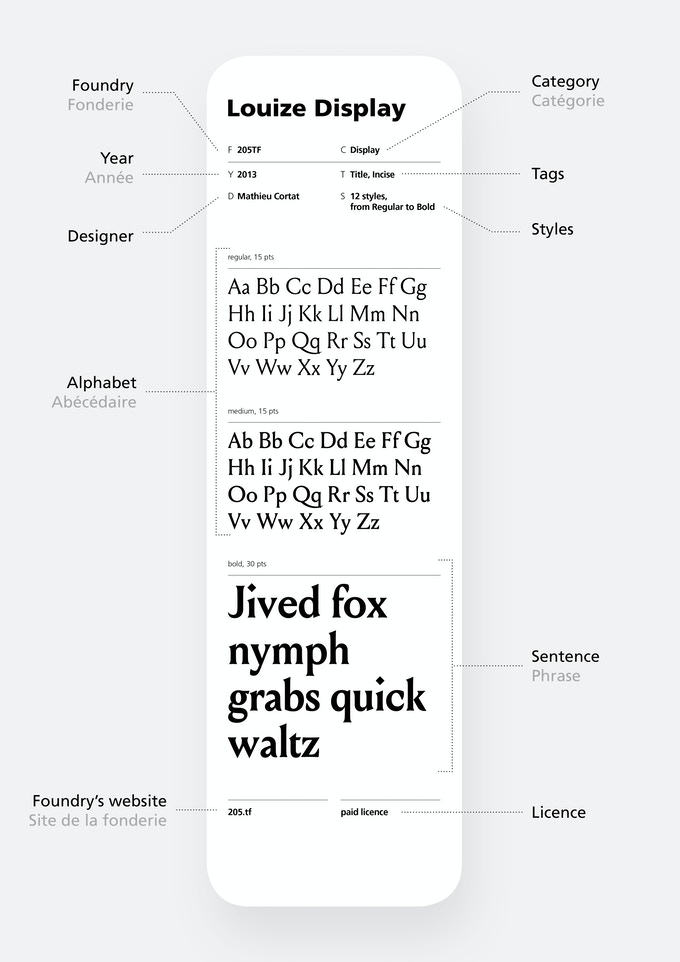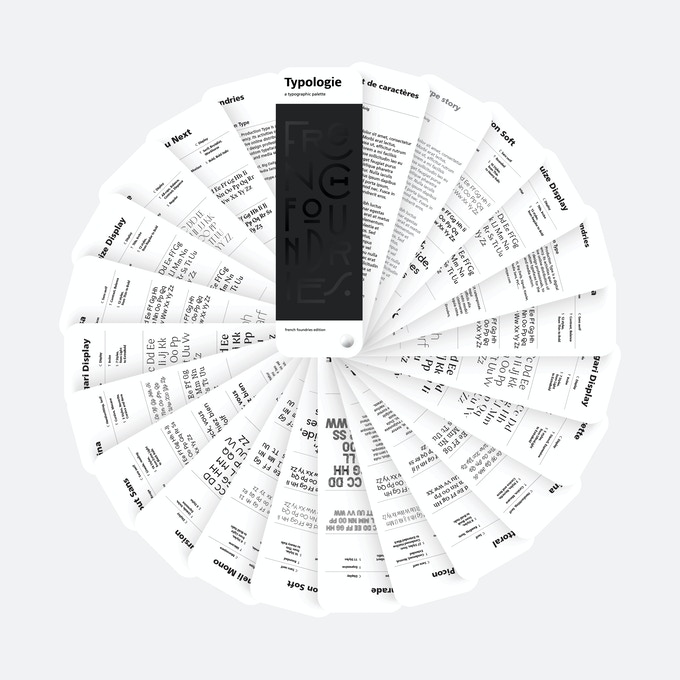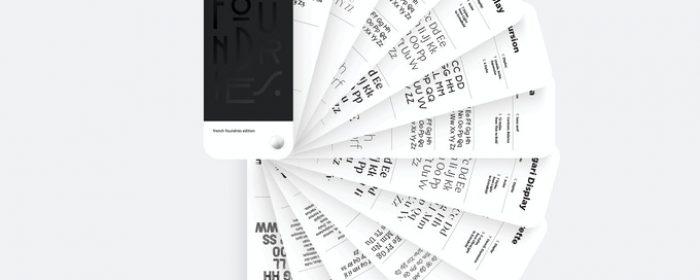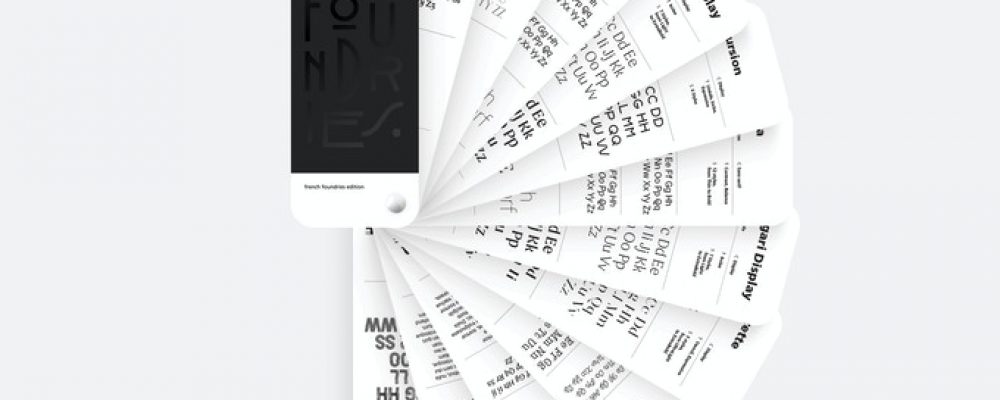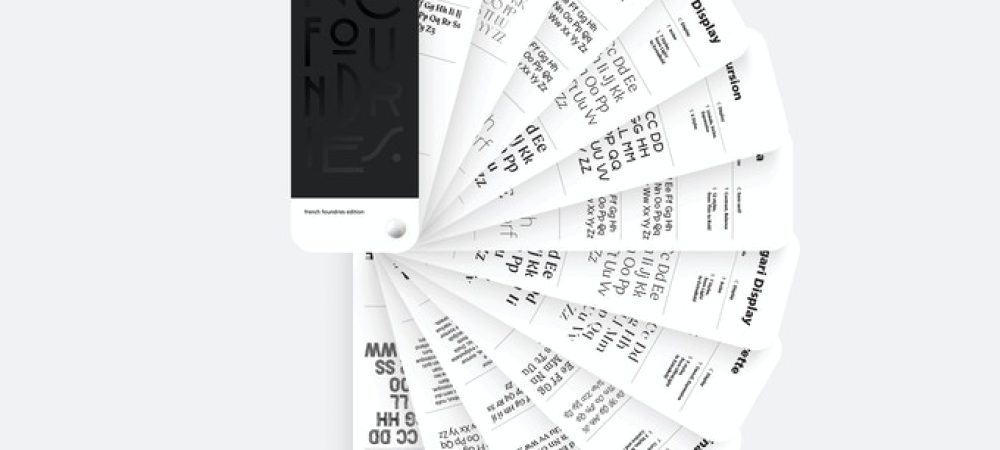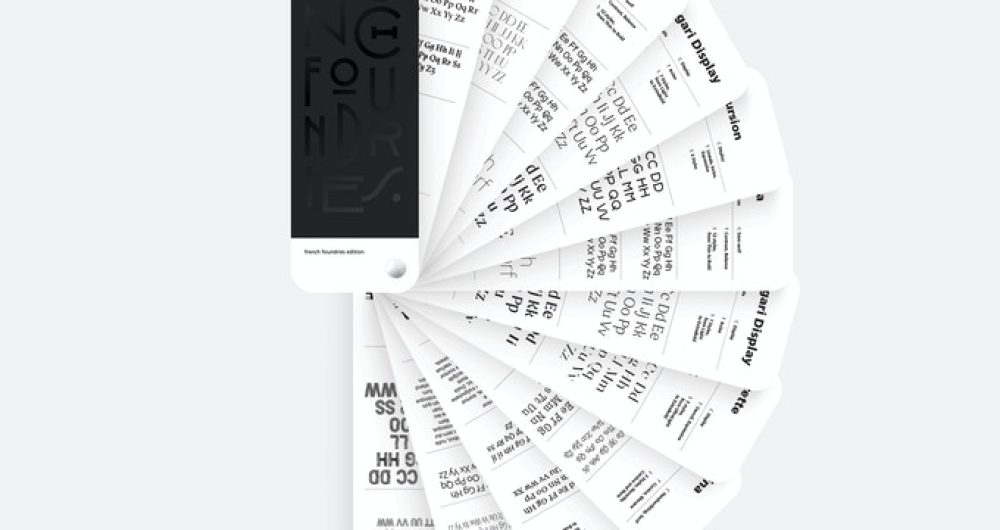
Un nuancier spécialement conçu pour les amoureux de la typographie
Si vous nous suivez régulièrement, vous connaissez notre goût particulier pour la belle typographie. En effet, la calligraphie est un art qui permet de laisser transparaître des émotions, un caractère, mais c’est surtout un formidable outil de communication.
Aujourd’hui je vous présente Typologie, un livre sous la forme d’un nuancier Pantone qui raconte les finesses et les histoires des typographies. Imaginé par Pierre-Yann Lallaizon, ce livre original vous transportera dans un nouvel univers typographique, vous forçant ainsi à sortir de votre zone de confort artistique. En effet, tous les créatifs ont leur propre palette de polices de caractères et ils sont, généralement, plutôt réticents au changement. C’est le constat que l’auteur a fait et qu’il à voulu briser à travers ce livre. Quelle meilleure combinaison pouvait-il y avoir entre un nuancier, représentation parfaite de la recherche d’un atout créatif (une couleur) et la typographie ?
Sa forme unique permet donc aux créatifs de faire matcher des typographies entre elles, et de trouver de nouvelles combinaisons facilement. Plus qu’un outil de travail, c’est également un bel objet qui est assez cool à poser dans sa bibliothèque ou sur son bureau. Le nuancier se décompose d’ailleurs en plusieurs catégories :
• Typographies Serif
• Typographies Sans Serif
• Typographies Display
• Typographies Monospace
• Typographies Handwriting
• Typographies Expressives
• Les fonderies